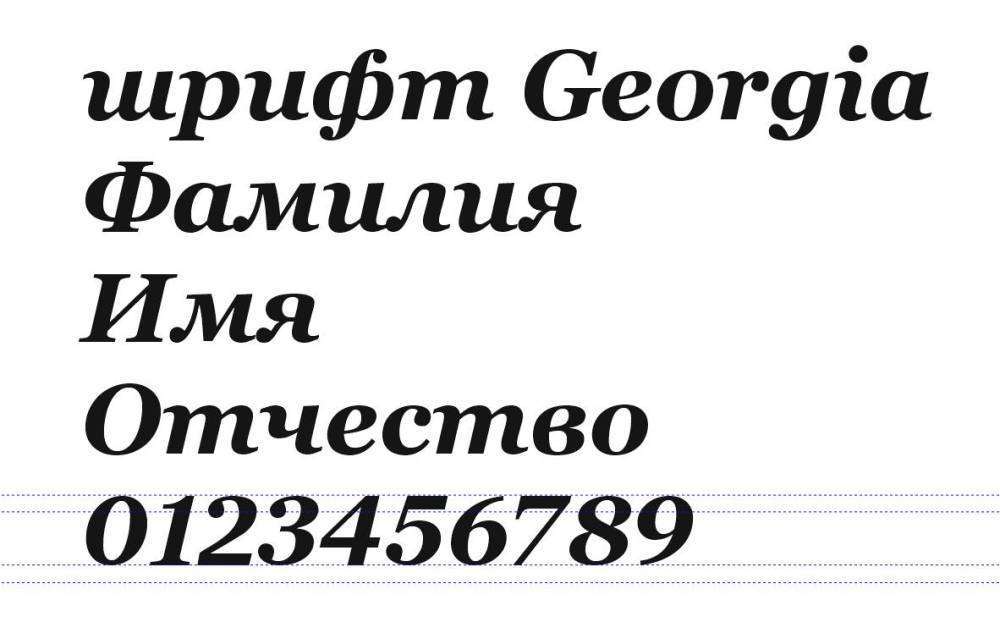
Популярный пост Aleksey-Yujakov Опубликовано 18 августа, 2022 Популярный пост Опубликовано 18 августа, 2022 выровнял цифры в одном из очень популярных шрифтов ,в системе что бы не переписался старый имя Memorial Art Georgia https://disk.yandex.ru/d/-tB1kKseh4Ow_Q 11 2